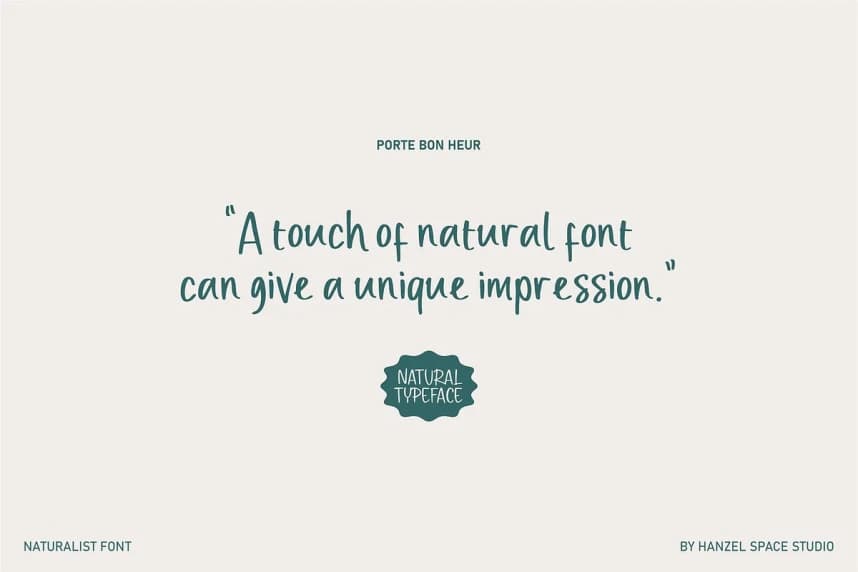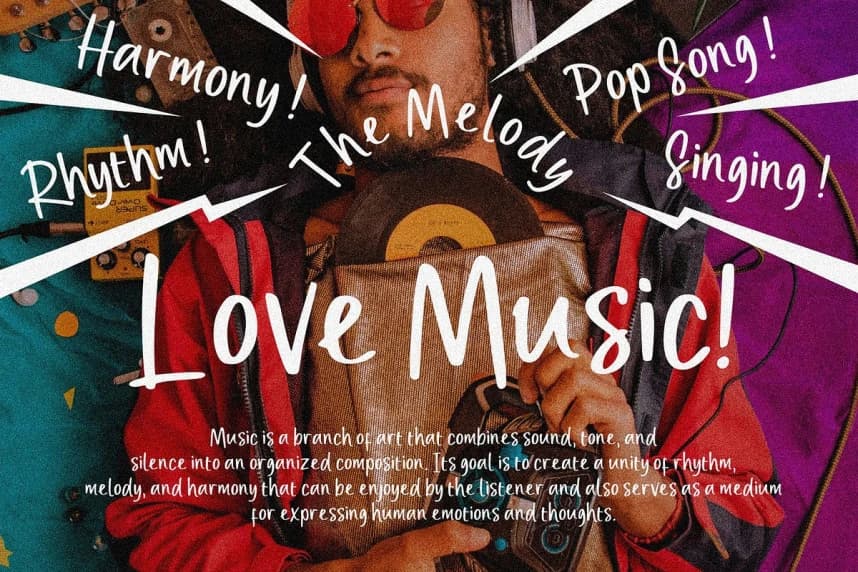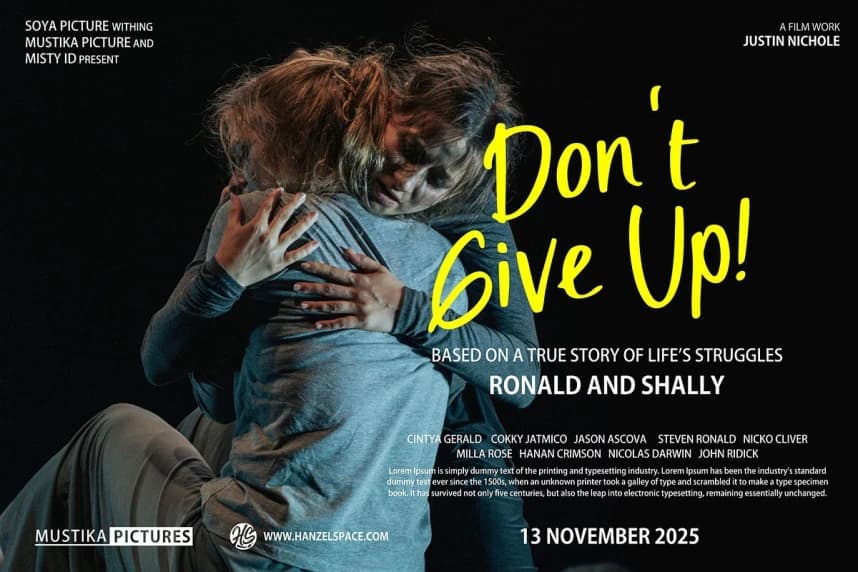
Porte Bon Heur Yazı Tipi
Porte Bon Heur Font - doğal bir el yazısı fontudur ve ifade dolu, hafif kusurlu bir el yazısı hissine sahiptir. Bu font benzersiz ve otantik bir hat sunar. Bu tür font özellikle logo ve başlıkta uygulanmak üzere mükemmel şekilde tasarlanmıştır.
Porte Bon Heur Font - doğal bir el yazısı yazı tipidir; ifade dolu, hafif kusurlu bir el yazısı hissine sahiptir. Bu yazı tipi benzersiz, özgün bir çizgi sunar. Bu yazı tipi özellikle logo ve başlıklar için uygulanmak üzere mükemmel şekilde tasarlanmıştır.